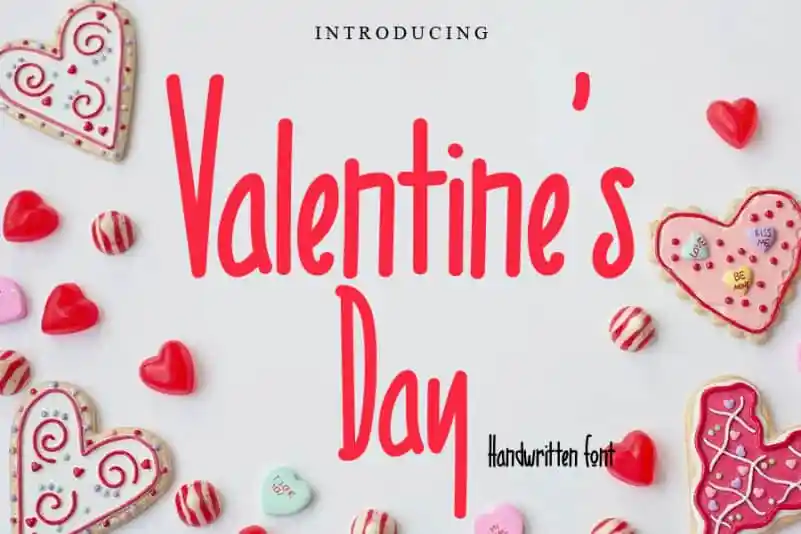
Avalie com prazer a “Valentine’s Day Handwritten Font”, uma elegante seleção de texto manuscrito ideal para o ambiente delicado e romântico do Dia dos Namorados. Essa fonte simples, fina e alta enriquece qualquer design gráfico que ele abrace, elevando-os ao topo da sofisticação e criatividade. Com seu formato elegante e versátil, a “Valentine’s Day Handwritten Font” se adapta facilmente a uma ampla variedade de projetos, desde cartões para o Dia dos Namorados até designs web e anúncios publicitários. Seja você um designer que busca trazer delicadeza e personalidade à sua arte ou um entusiasta do design gráfico em busca de algo inovador, essa fonte é certamente seu escolhido.